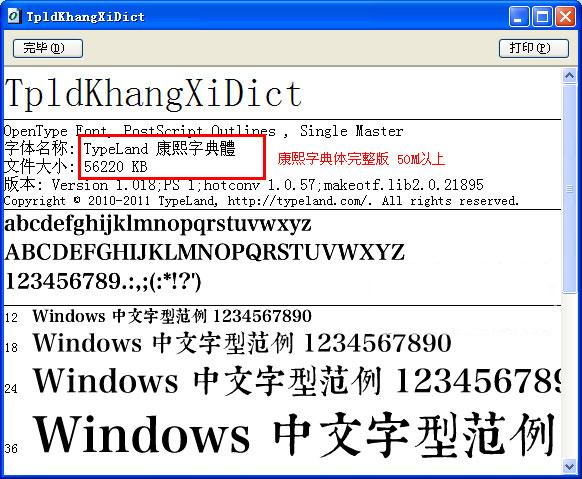
康熙字典體完整版是一款字形優(yōu)美、大方得體的中文簡體漢字,完整版字體大小50M以上,字體筆鋒犀利,熱情奔放,適用于廣告設(shè)計、平面設(shè)計、標(biāo)題正文、書法繪畫等領(lǐng)域,使用時請選擇“TpldKhangXiDict”即可,喜歡的朋友快下載收藏吧。
“康熙字典體” 基于道光七年奉旨重刊版制作,按音譯篩除重復(fù)字頭后,共計收錄漢字 4,7037 個,并同時參照其它版本校正。將原書以 1200dpi 進(jìn)行掃描并進(jìn)行摳字,將原書中的文字分別提取出來,進(jìn)行一些修繕后轉(zhuǎn)成矢量輪廓 (Auto-traced),并非如一般字體設(shè)計那樣手動繪制矢量曲線。